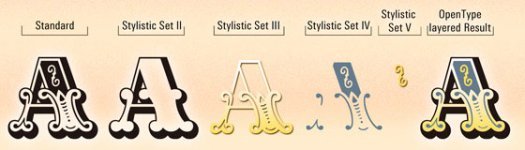
LinoLetter 2007/12 - Madame
Linotype のメールマガジン、LinoLetter の今月号が届いた。メールマガジンといっても、内容はまるまる下のページで読める。
ここで紹介されていた Madame というフォントの OpenType 版は、普通のグリフとは別に、それを4つのレイヤに分解したグリフが入っているらしい。で、OpenType のいろいろな機能に対応したアプリケーション*1だと、レイヤごとに色をつけて多色刷りができるんだとか。
The OpenType font is very powerful. The font offers the ability to set each letter as either a single glyph, or to set each character by layering up to four glyphs over top of one another to create polychromatic type! These layering elements are for use as decoration for the inner spaces of the respective character. The easy use of this feature is only possible thanks to OpenType and OpenType-savvy applications.
Madame - Linotype Font Feature
OpenType にこんな機能があるとは知らなかった。なんか版画みたいでおもしろい。
*1:LinoLetterに “These layering elements may be used to decorate for the inner spaces of their respective characters in OpenType-savvy applications like the Adobe CS line or QuarkXPress 7.” と書いてある。まぁどれも持ってないんだけどさ。